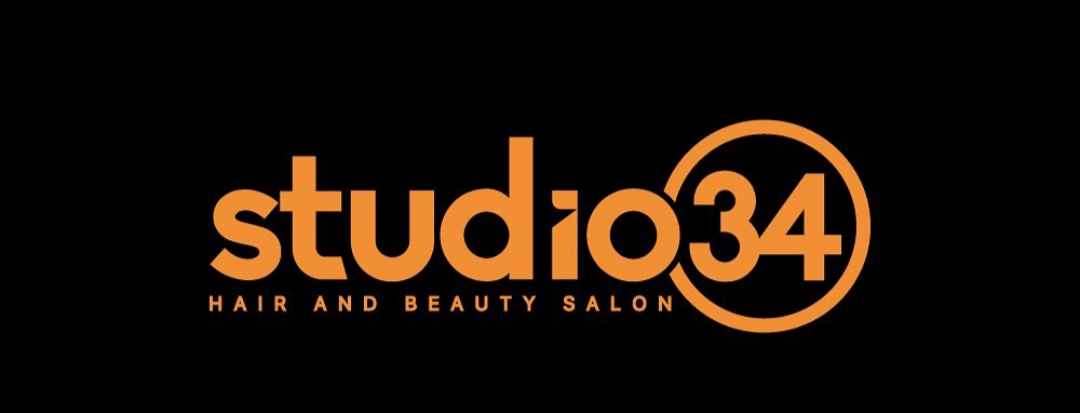
✒️ Font Arayışı
Resimdeki gibi font arayışım bulunmakta. i harfinin çentikli olduğu fontlar var mıdır?
hocam bu fonttan ziyade tasarım gibi duruyor
Bunlar genelde tasarım çizim oluyor, font olarak yapanlarda bulunuyor fakat genelde özel font dağıtılmaz ya da dağıtılırsa paralı olarak dağıtılır.
Görseldeki font
türevi bir fonttur. i ve t harfinde ve muhtelif bazı yerlerdeki düzenlemeler vectörel olarak düzenlenmiştir.